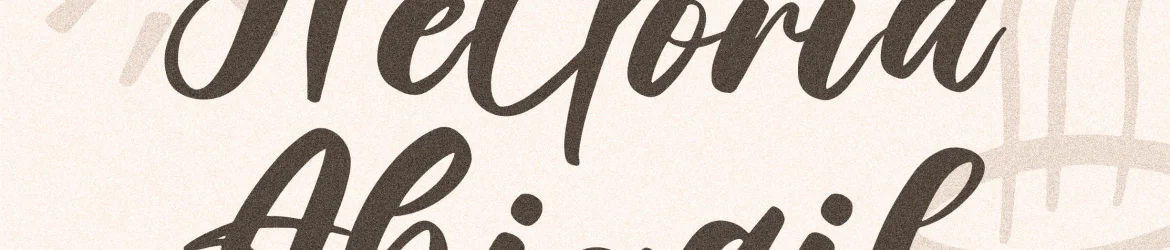
Helloria Abigail Font – Download Grátis
A fonte ‘Helloria Abigail’ é perfeitamente adequada para projetos onde a mão escrita adiciona aquela pitada especial de luxo e personalidade necessária. Seja ela uma marca inovadora, um design de casa cuidadosamente pensado ou até mesmo uma linda capa de livro, essa fonte oferece um toque autêntico que combina perfeitamente com esses projetos. Ideal para criações como cartões de convite, embalagens, artefatos para o lar e até mesmo para etiquetas e marcas personalizadas, a fonte ‘Helloria Abigail’ enriquece qualquer projeto, tornando-o único e imediatamente reconhecível. Além disso, sua utilidade em vários ambientes de criação – desde desenhos gráficos avançados até simples cartões da casa – faz dela uma opção versátil para designers que buscam complementar suas ideias com um toque delicado e autêntico. Com a fonte ‘Helloria Abigail’, você pode transformar seus projetos de forma imediatamente reconhecível, criando designs que chamam atenção e se destacam em qualquer formato ou plataforma. Afinal, uma fonte escrita à mão não apenas dá um toque único às suas criações, mas também oferece a oportunidade de transmitir um sopro de personalidade inimitável para cada projeto.